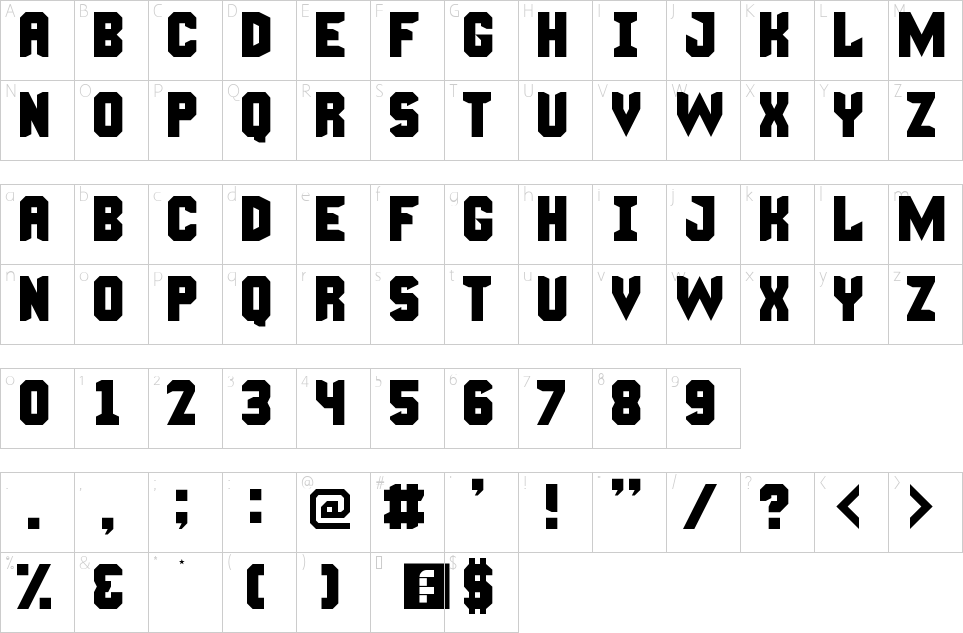
Manly Man Font | 1001 Free Fonts – Fonte Grátis
A fonte ‘Manly Man’ é uma criação moderna e poderosa, especialmente adequada para designers que buscam uma fonte bold e marcante para suas criações. Desenhada por Chequered Ink, esta font é ideal para uso em aplicações Windows e Mac, e tem sido baixada 6.907 vezes. Seja para criar títulos impressionantes ou destacar elementos importantes em sua próxima peça de design, ‘Manly Man’ certamente irá fazer seu trabalho. Seja você um designer profissional ou iniciante, esta fonte gratuita e poderosa é uma ótima opção para deixar seu trabalho de design ainda mais impressionante.